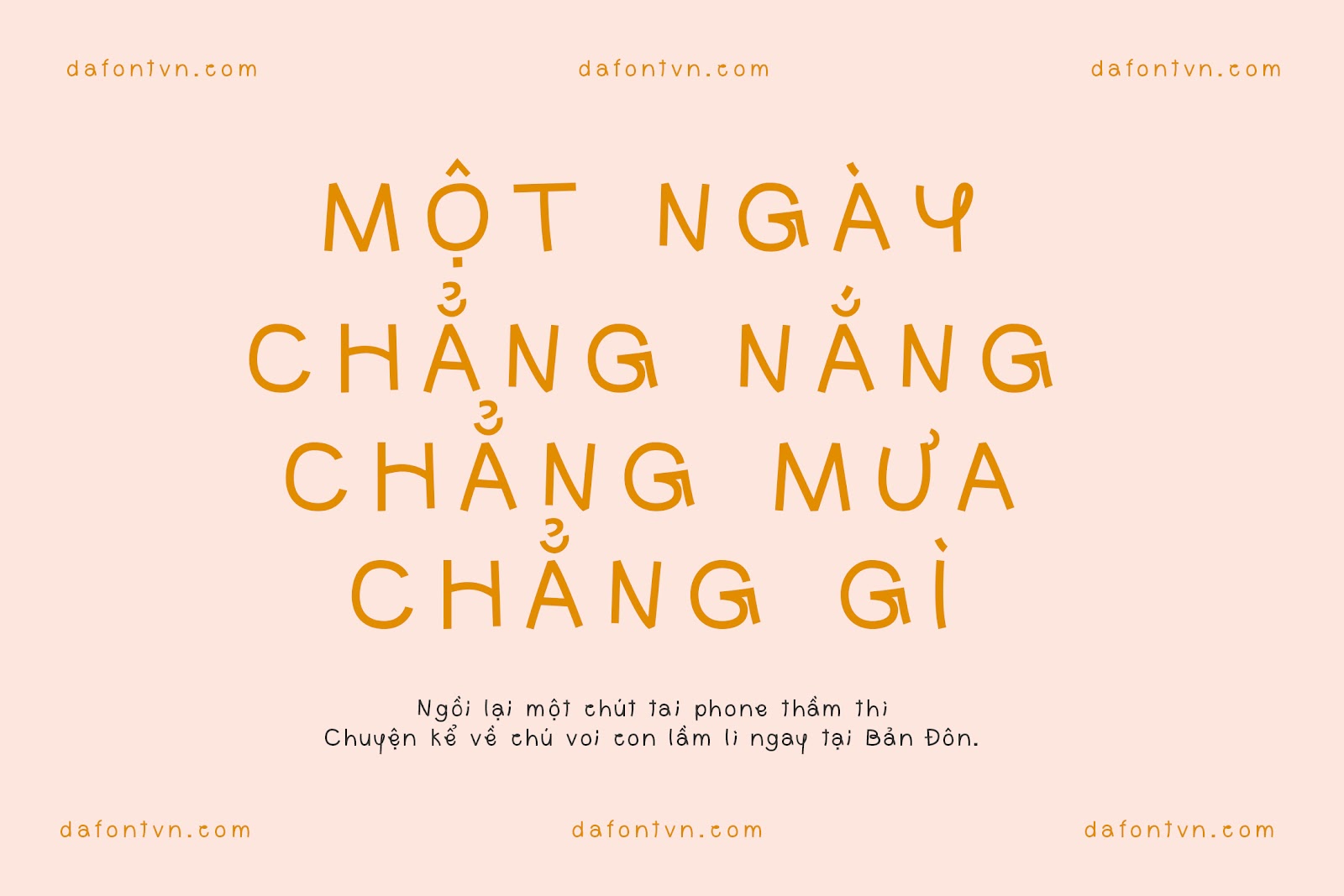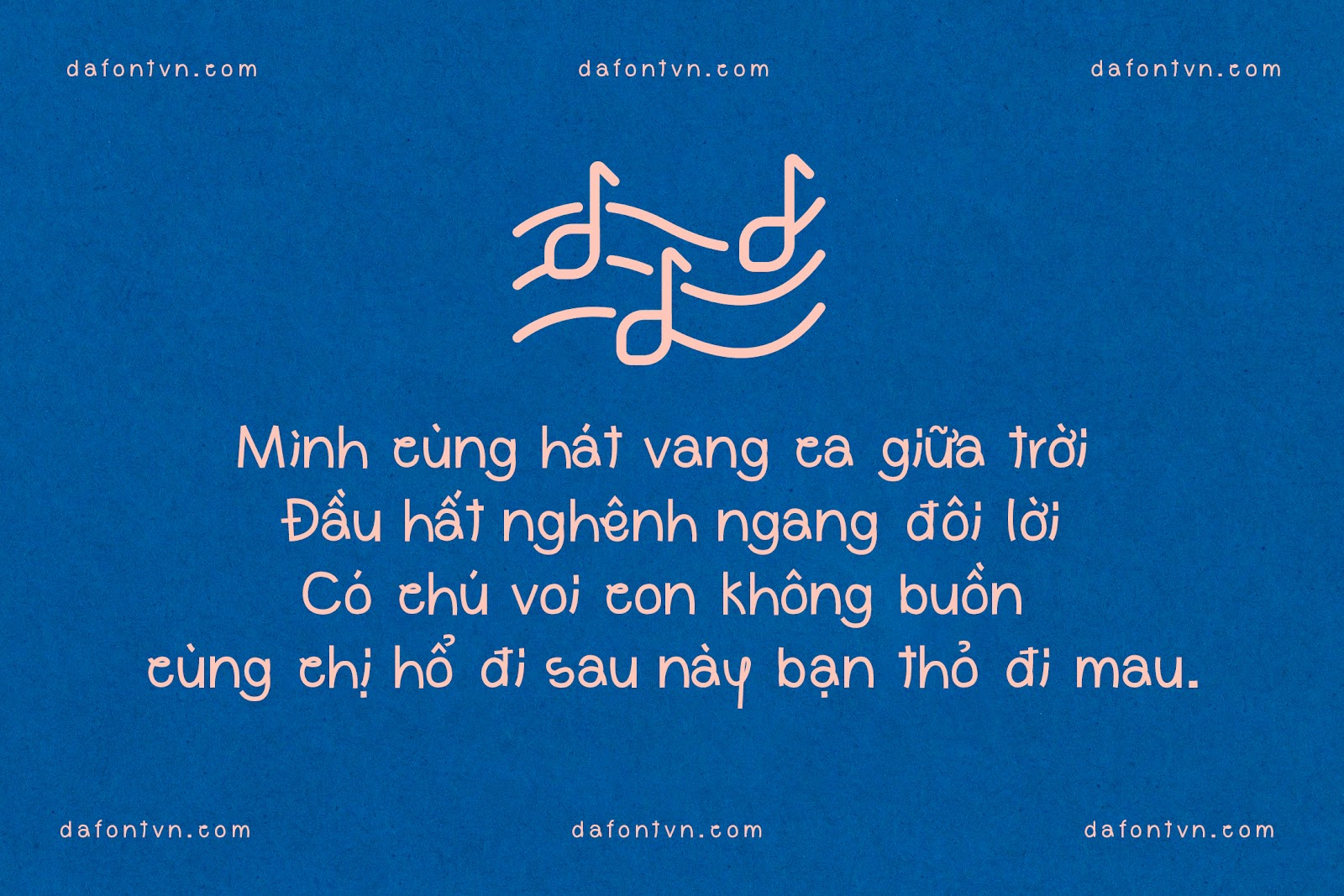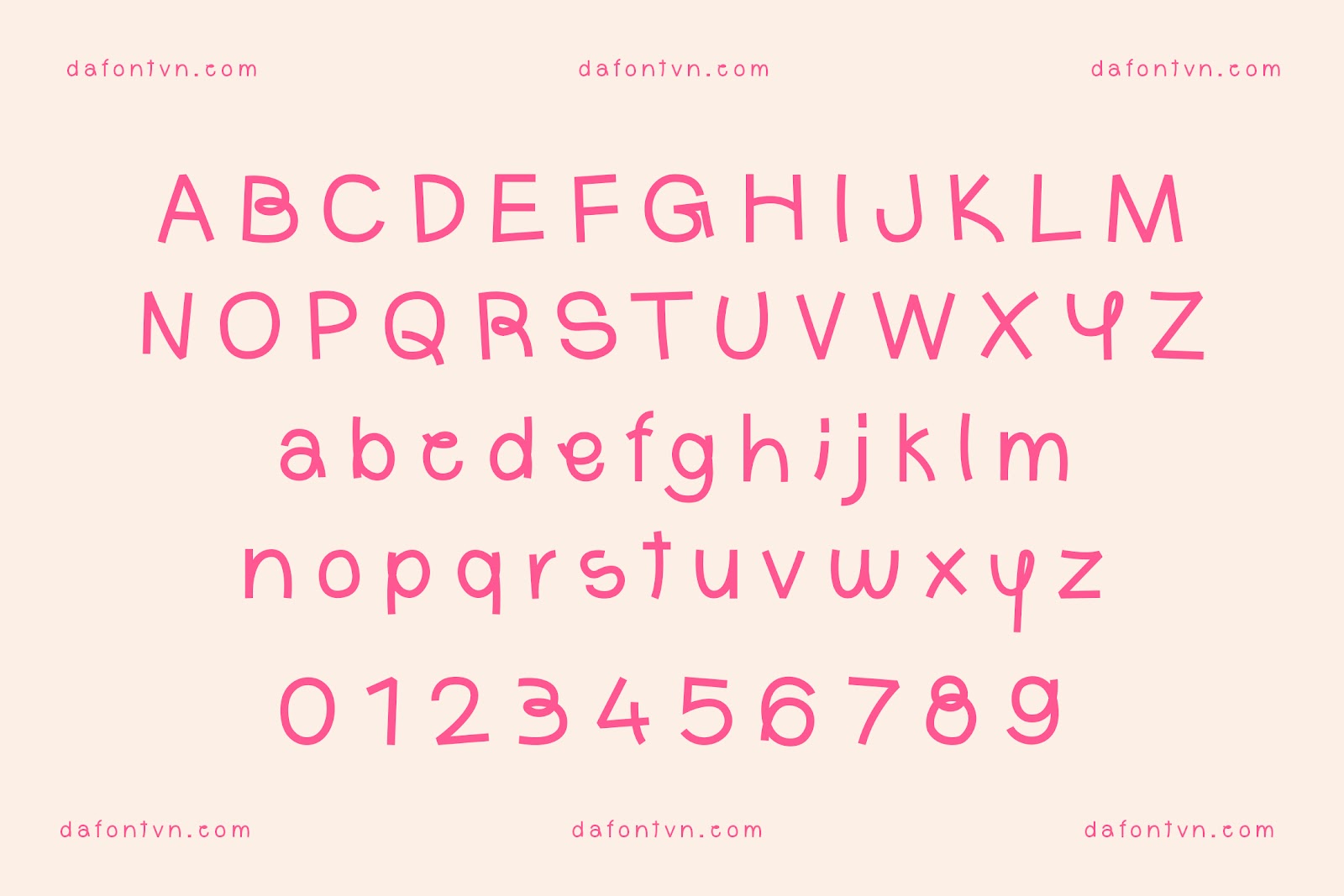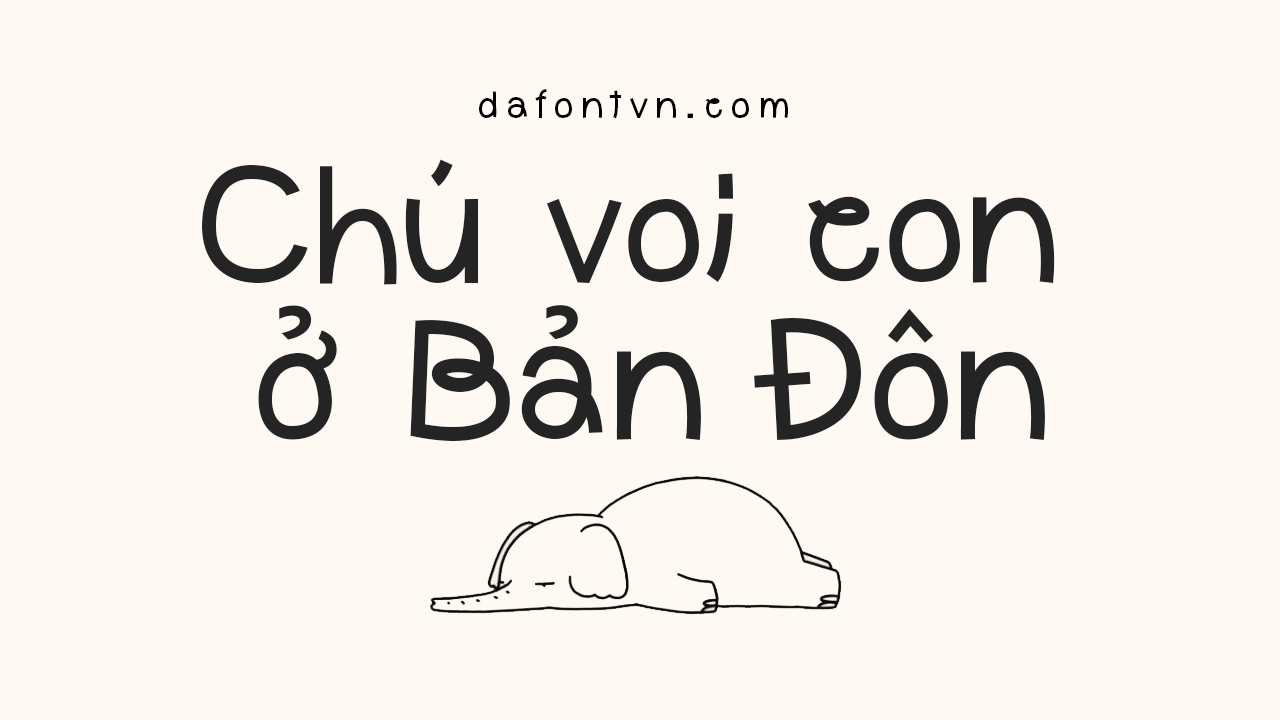
Boris là kiểu phông chữ hiển thị được thiết kế bởi Giulia Boggio với các ký tự được thiết kế mang phong cách vui nhộn. Nó hoàn hảo cho nhiều các thiết kế khác nhau như tạp chí, thiệp, áp phích, kết hợp với hình minh họa và bất cứ thứ gì bạn cần để có vẻ ngoài vui tươi mà không làm mất đi tính dễ đọc.